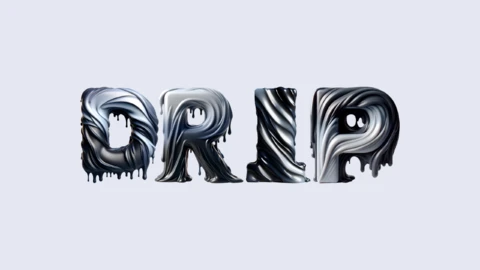
Police de caractères en forme de goutte d'eau
Créez un effet de texte "Instagram Vip Bio Stylish Font" police caractères forme goutte d'eau grâce à notre générateur de polices personnalisées en ligne.